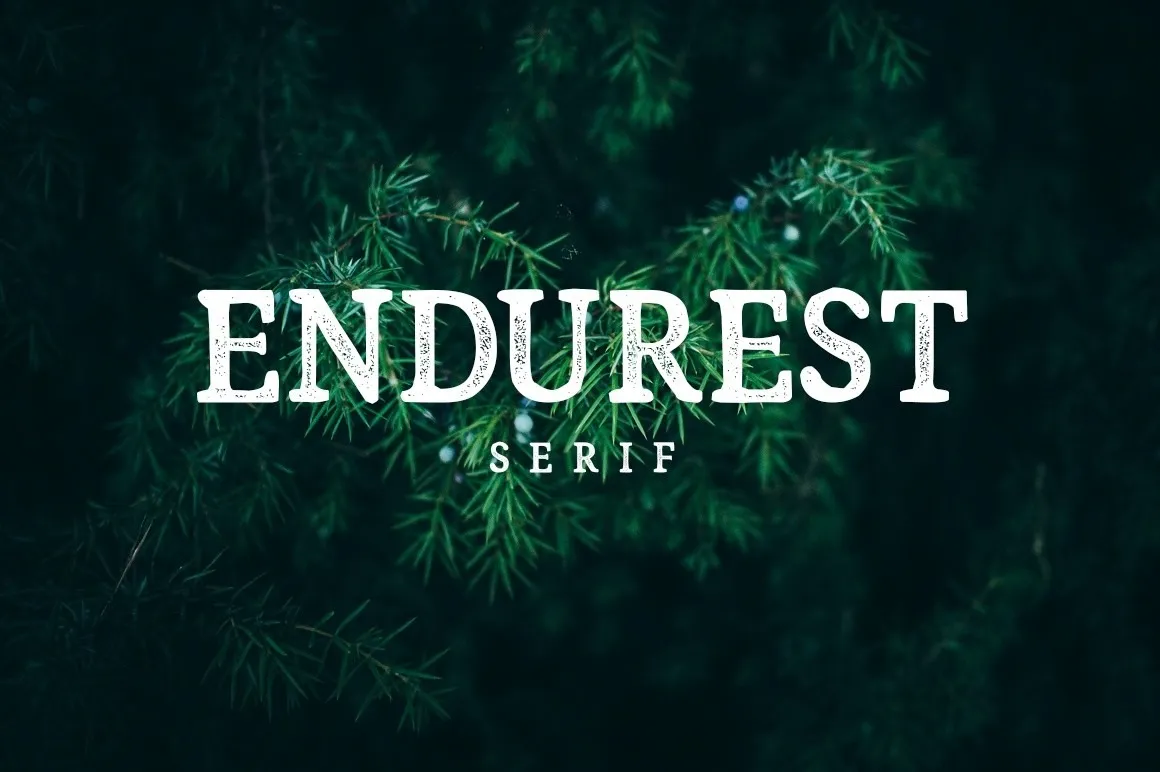
A Endurest Font é uma elegante serif moderna que combina elementos vintage e a essência contemporânea. Construída pelos criativos designers do The Branded Quotes, ela foi projetada para resistir às mudanças rápidas do mundo digital. Inspirada nos gráficos da era de Sir Raymond DaBoll, mas revigorados com toques modernos como marcadores digitais e materiais como vidro acrílico, a fonte garante um equilíbrio perfeito entre as alturas e espaçamentos dos caracteres. Com duas estilos distintas, esta serif moderna não apenas oferece uma versatilidade impecável para uso em diversos formatos de texto, mas também traz uma paleta única que reflete a contemporaneidade. Suavemente vintage, mas com um toque de inovação e frescura, a Endurest é perfeita para aqueles que desejam um tom elegante e sofisticado sem perder o toque moderno. Ideal tanto para usar em ambientes digitais como impressos, ela se adapta à sua necessidade de estilo com uma capacidade de combinação automática entre tamanho e espaçamento. Este é a fonte que você precisa para manter um olhar contemporâneo enquanto preserva o encanto do passado.